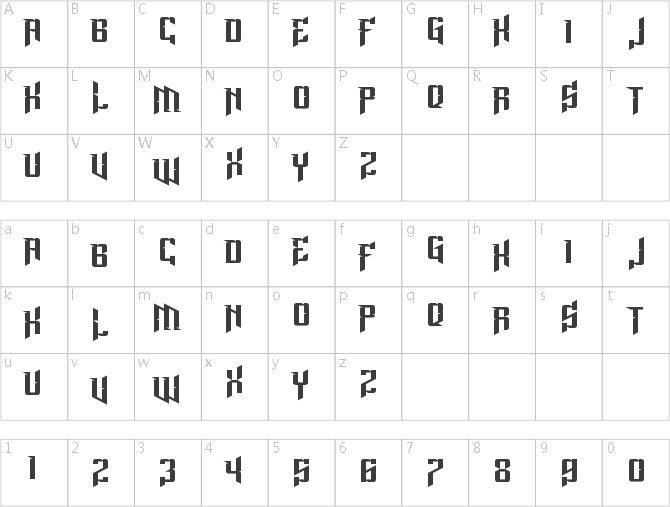
Lord-Juusai-Rises-Regular
Lord-Juusai-Rises-Regular介紹
Lord-Juusai-Rises-Regular字體字庫是一款讓人賞心悅目、百看不厭的英文字體,適合各類廣告和產品包裝設計應用,字體大小0.02MB,格式為ttf字體,上傳用戶是舒甜咖啡,作者/版權方為未知